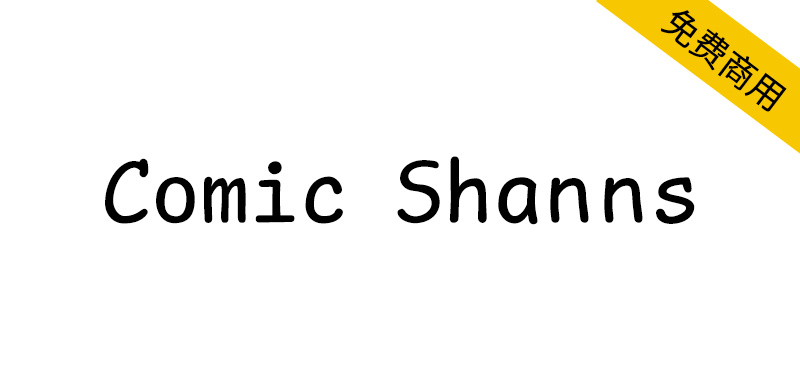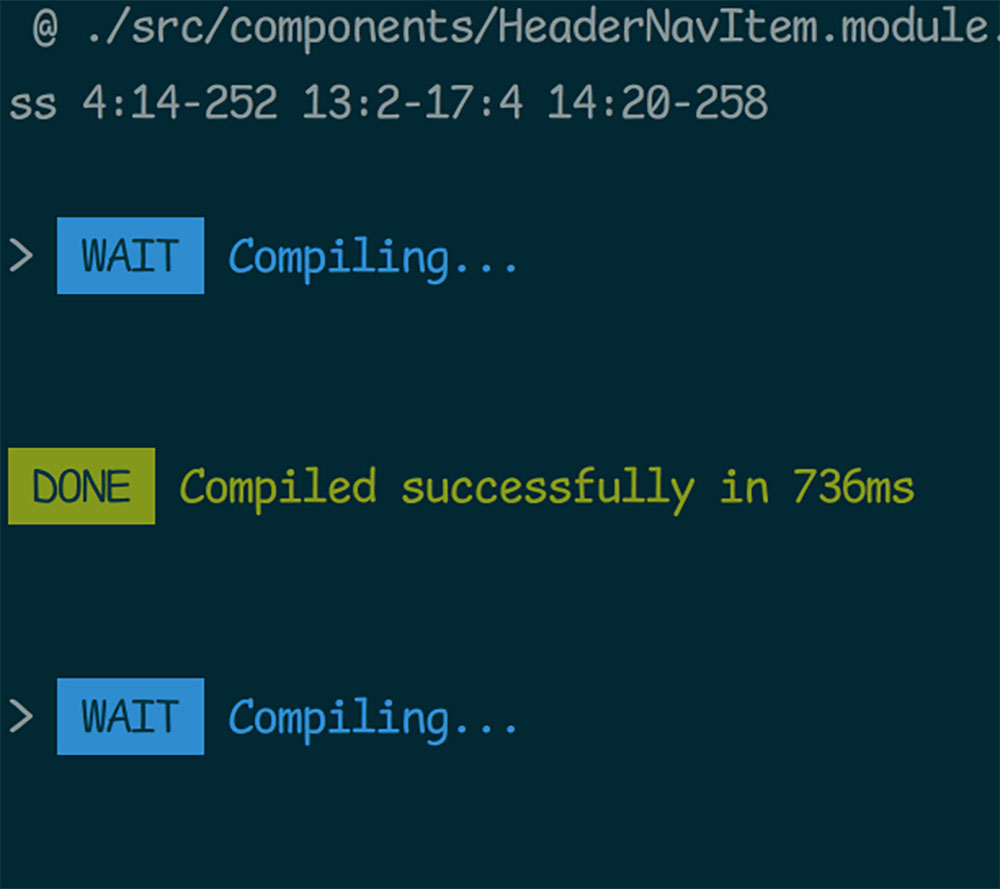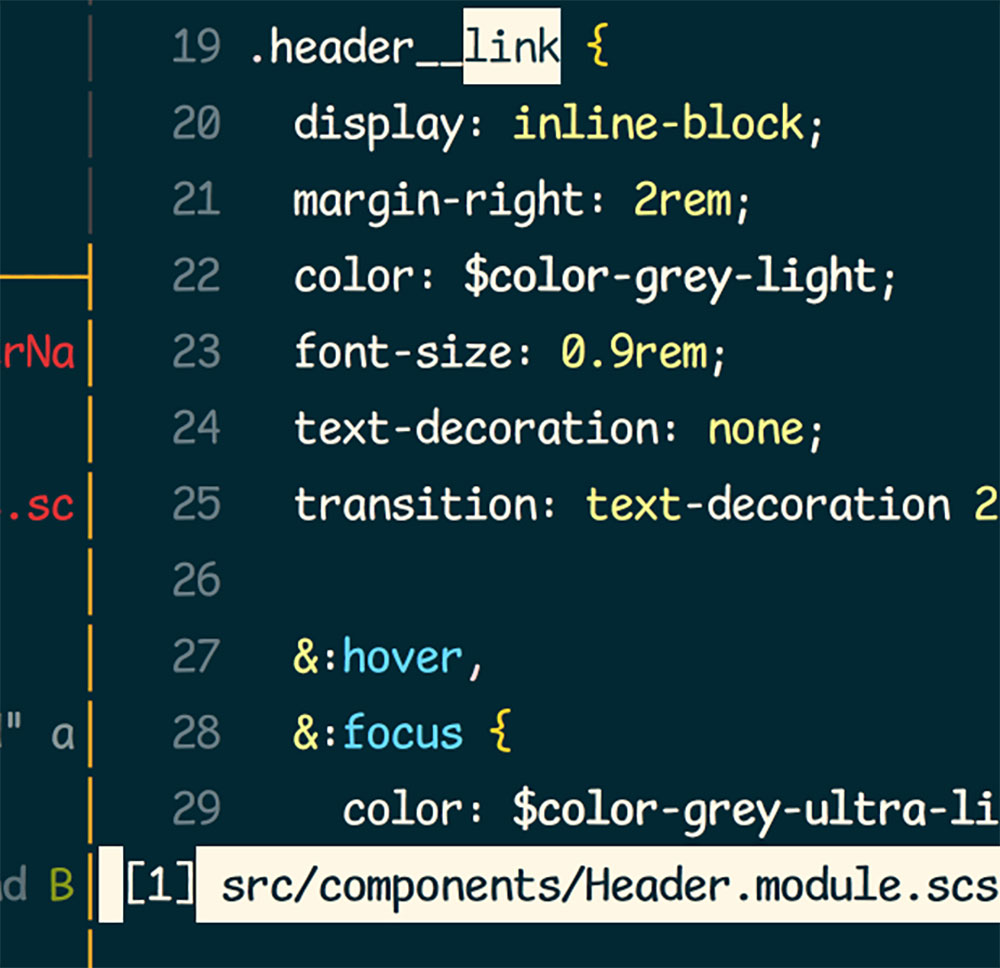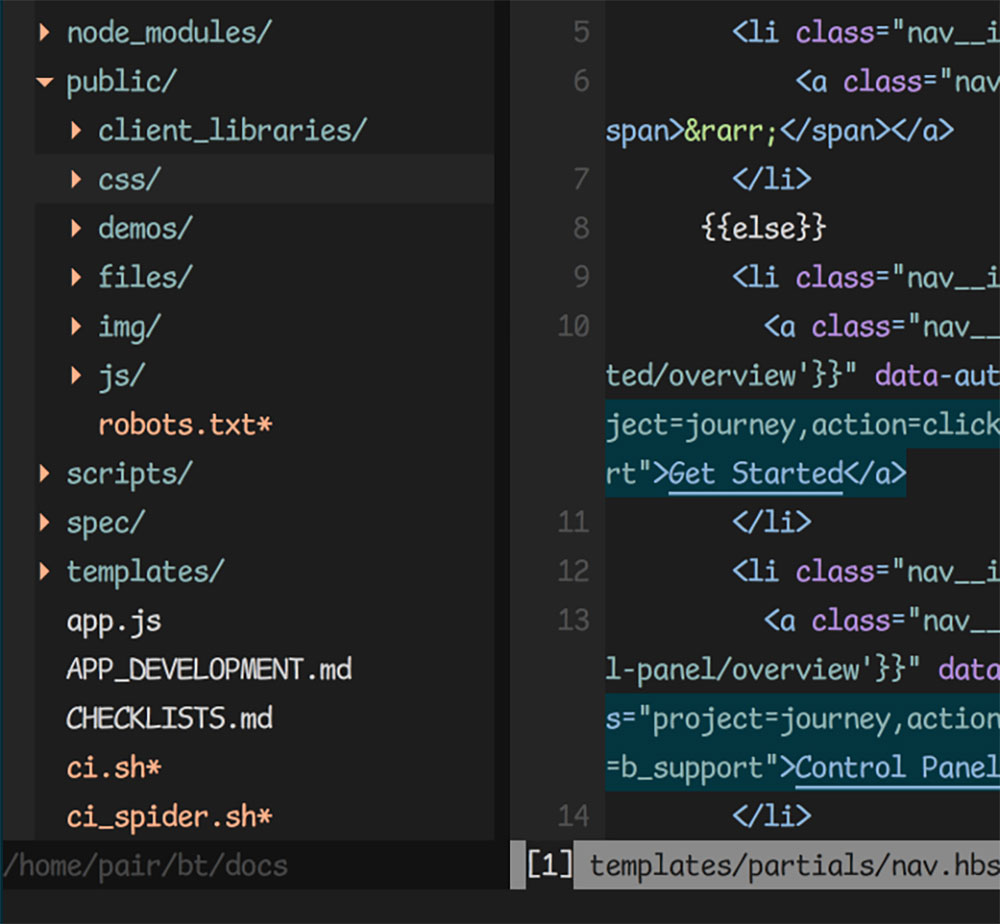
你是那种会在演示文稿中使用Comic Sans字体的人吗?是否每个夜晚都辗转反侧,梦想着能用Comic Sans字体编写代码——让代码像你心爱的幻灯片那样赏心悦目?别再等待了!现在为你隆重推出Comic Shanns!这款受Comic Sans启发的等宽字体,即将登陆你身边的终端或代码编辑器!
Comic Shanns字体看起来像什么?就像有人把Comic Sans改成了等宽字体,但改得有点蠢萌蠢萌的。
Comic Shanns Mono与Comic Shanns的区别:Comic Shanns Mono 是基于 Comic Shanns 调整了字距参数,并新增了更多字符。
Are you the kind of person that uses Comic Sans in presentations? Do you lie awake every night dreaming about a world where you could write your code in Comic Sans where it looks just as beautiful as on your dear presentations? Wait no more! I present to you Comic Shanns! The Comic Sans inspired monospaced font that's coming to a terminal or editor near you!
What does it look like?Like if someone made a dumbass version of Comic Sans that is monospaced.
Comic Shanns Mono by Jesus Gonzalez, which is based on Comic Shanns v2 but with metrics adjusted and with more additional characters.